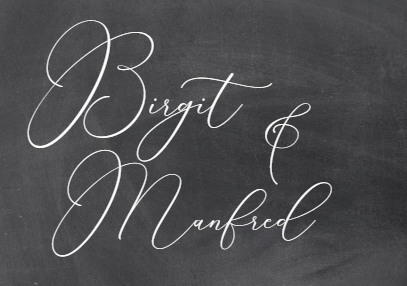
Verschnörkelte Schriftart von Sendmoments
für meine Hochzeitsvorbereitungen suche ich nach der Kalligraphie /Schriftart von Sendmoments:
Bei den Einstellungen ist die Schriftart so klein geschrieben, dass ich sie nicht entziffern kann.
Ich benötige diese um Vorlagen anzufertigen anhand dieser eine Tafel beschrieben werden soll.